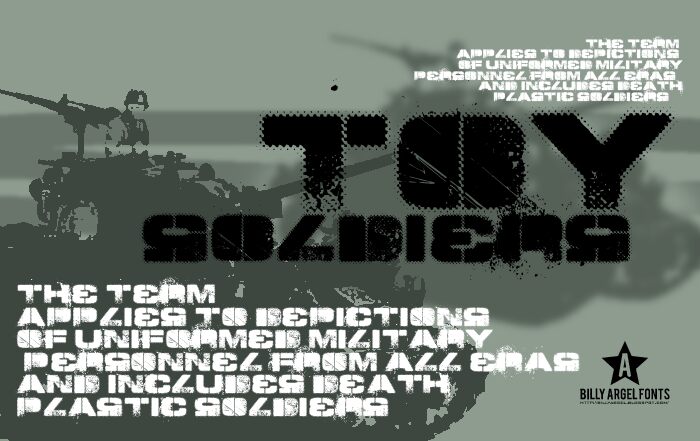
Toy Soldiers, bezpłatny wojskowy krój pisma typu display autorstwa Billy'ego Argela z 2008 roku, nadaje wielkim literom surowy, koszarowy charakter. Znaki sprawiają wrażenie przybitych pieczątką, zdartych i nadszarpniętych zębem czasu – ze szczerbami jak z szablonu, ziarnistą teksturą sprayu i zadrapaniami, dzięki czemu cały font wygląda na mocno wyeksploatowany, a nie starannie narysowany.
Idealnie pasuje do plakatów, tytułów gier, ulotek z motywami akcji, okładek albumów i opakowań, w których pożądany jest klimat wojskowego rozkazu. Jako darmowy font, sprawdza się szczególnie dobrze w krótkich nagłówkach, kartach tytułowych i znakach graficznych typu badge, ponieważ dzięki poszarpanej teksturze i surowemu, wojskowemu rytmowi, przekazuje wszystko, czego potrzeba, nawet w zaledwie kilku literach.